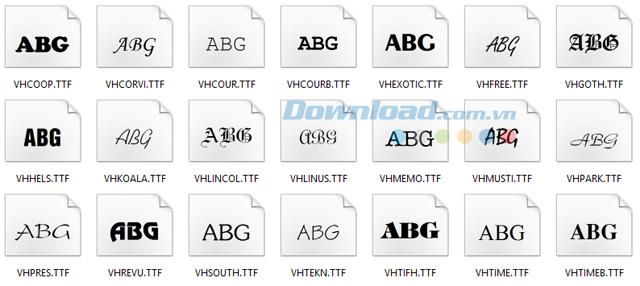
Bộ Font TCVN3 đầy đủ là một bộ font chữ tiếng Việt tiêu chuẩn, từng rất phổ biến ở Việt Nam. Mặc dù hiện nay Unicode đã trở thành chuẩn mã hóa chính thức và được sử dụng rộng rãi hơn, bộ font TCVN3 vẫn giữ một vị trí nhất định, đặc biệt trong việc hỗ trợ hiển thị và đọc các tài liệu cũ hoặc đáp ứng những yêu cầu đặc biệt. Bài viết này sẽ cung cấp thông tin chi tiết về bộ font TCVN3, hướng dẫn tải về và cài đặt, cũng như giải thích một số đặc điểm nổi bật và những điểm cần lưu ý khi sử dụng.
Giới thiệu về Bộ Font TCVN3
Bộ Font TCVN3 bao gồm các font chữ cơ bản như .VNTime, .VNArial và một số font khác thuộc họ TCVN3. Đây là một bộ mã hóa tiếng Việt được sử dụng rộng rãi trước khi Unicode trở nên phổ biến. Bộ font này hỗ trợ đầy đủ các ký tự tiếng Việt, bao gồm các dấu thanh (sắc, huyền, hỏi, ngã, nặng) và các nguyên âm đặc biệt như ắ, ẹ, ủ, ơ, ư. Tuy nhiên, do là một chuẩn mã hóa cũ, cách hiển thị và gõ chữ trong TCVN3 khác biệt so với Unicode, điều này có thể gây bất tiện cho người dùng quen với phương pháp gõ hiện đại hơn.
Đặc điểm nổi bật của Bộ Font TCVN3:
Hỗ trợ Tiếng Việt đầy đủ: Bộ font TCVN3 bao gồm tất cả các ký tự tiếng Việt cần thiết, đảm bảo hiển thị chính xác các dấu thanh và các nguyên âm đặc biệt. Mặc dù độ phủ ký tự không rộng bằng Unicode, nhưng vẫn đủ dùng cho hầu hết văn bản tiếng Việt thông thường.
Mã hóa đặc biệt cho tiếng Việt: TCVN3 sử dụng hệ thống mã hóa riêng cho tiếng Việt, khác biệt so với các hệ thống mã hóa quốc tế khác. Điều này đảm bảo hiển thị chính xác các ký tự tiếng Việt trong môi trường sử dụng bộ font này.
Đa dạng kiểu dáng phông chữ: Mặc dù không đa dạng bằng các bộ font hiện đại, bộ TCVN3 thường bao gồm nhiều kiểu dáng phông chữ khác nhau, cho phép người dùng tùy chọn để tạo ra văn bản đẹp mắt và phù hợp với mục đích sử dụng.
Khả năng tương thích cao: Bộ font TCVN3 tương thích với nhiều hệ điều hành, bao gồm Windows XP, Vista, 8 và 10, và các phần mềm xử lý văn bản phổ biến. Tuy nhiên, cần chú ý lựa chọn bộ gõ tiếng Việt phù hợp, ví dụ như Unikey hay Vietkey, để đảm bảo khả năng hiển thị và gõ chính xác. Việc lựa chọn chế độ gõ TCVN3 trong phần mềm gõ là bắt buộc.
Lưu ý quan trọng:
Khi sử dụng TCVN3, bạn sẽ nhận thấy sự khác biệt đáng kể so với việc gõ chữ Unicode. Một số từ sẽ được gõ và hiển thị khác so với cách gõ thông thường. Ví dụ, “lò dùng sóng” có thể thành “lũ dựng súng”, “lè nhè” thành “lố nhố”, v.v… Điều này là do sự khác biệt trong bảng mã giữa TCVN3 và Unicode. Do đó, bạn cần làm quen với cách gõ và hiển thị này nếu muốn sử dụng TCVN3 hiệu quả. Bộ font này thường được sử dụng cho các tài liệu cũ, hoặc trong những trường hợp đặc biệt yêu cầu sử dụng chuẩn mã hóa này.
Kết luận:
Mặc dù Unicode đã trở thành chuẩn mã hóa chính thống, bộ font TCVN3 vẫn có giá trị sử dụng nhất định trong một số trường hợp cụ thể. Việc hiểu rõ đặc điểm và cách sử dụng bộ font này sẽ giúp bạn dễ dàng xử lý các tài liệu sử dụng chuẩn mã hóa TCVN3 và đáp ứng được các yêu cầu đặc biệt. Tuy nhiên, cho các dự án mới và công việc hàng ngày, sử dụng Unicode vẫn được khuyến khích vì tính tương thích rộng rãi và độ phủ ký tự lớn hơn.